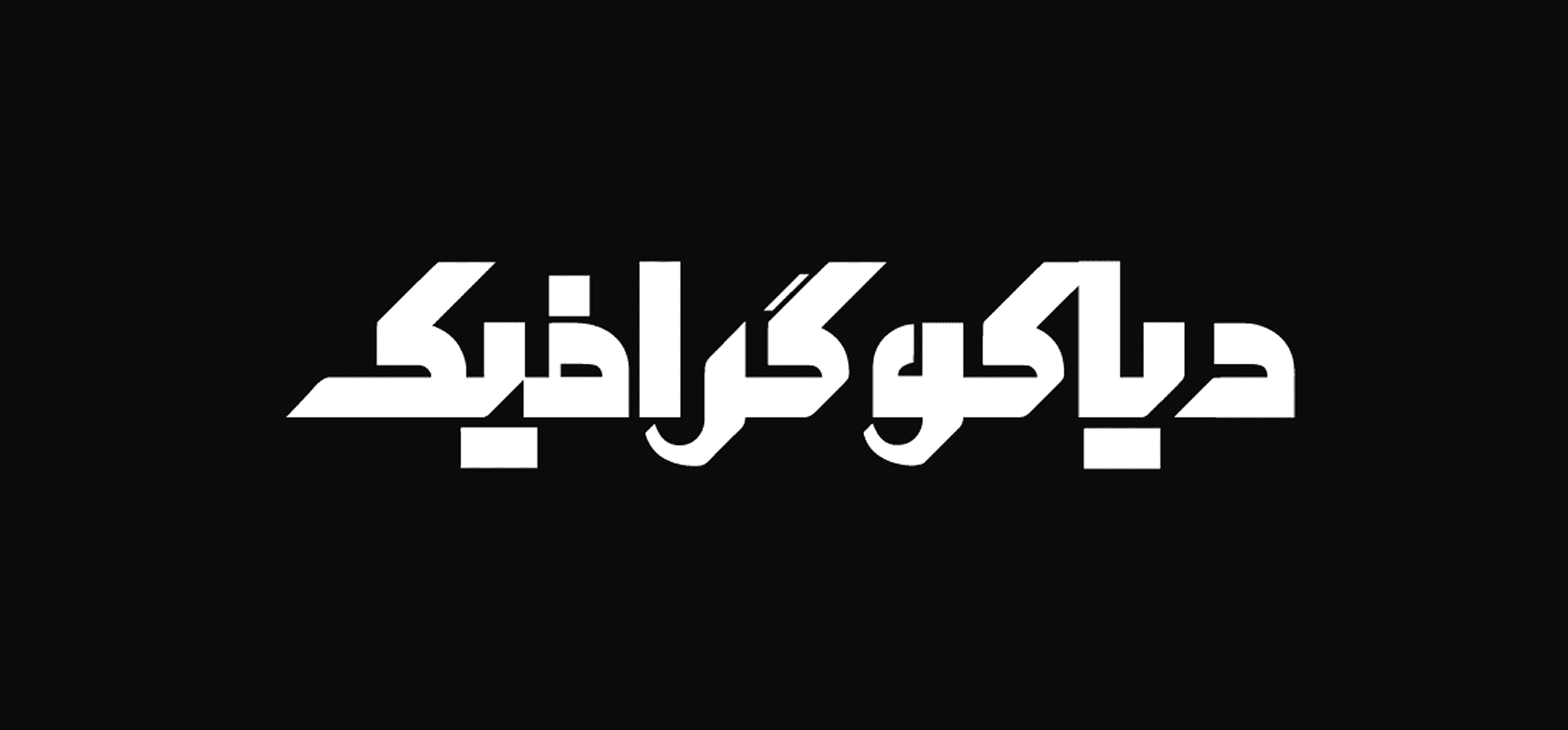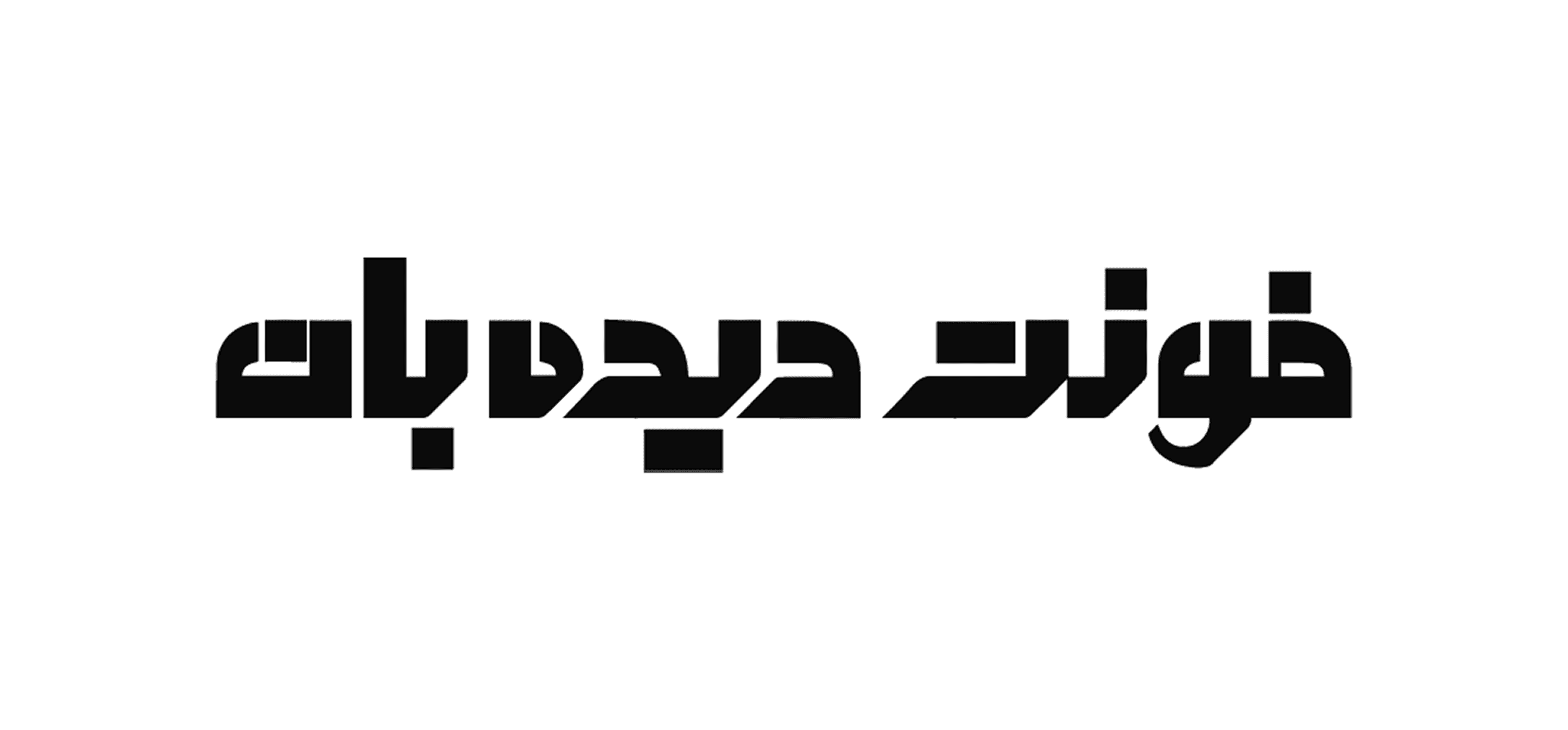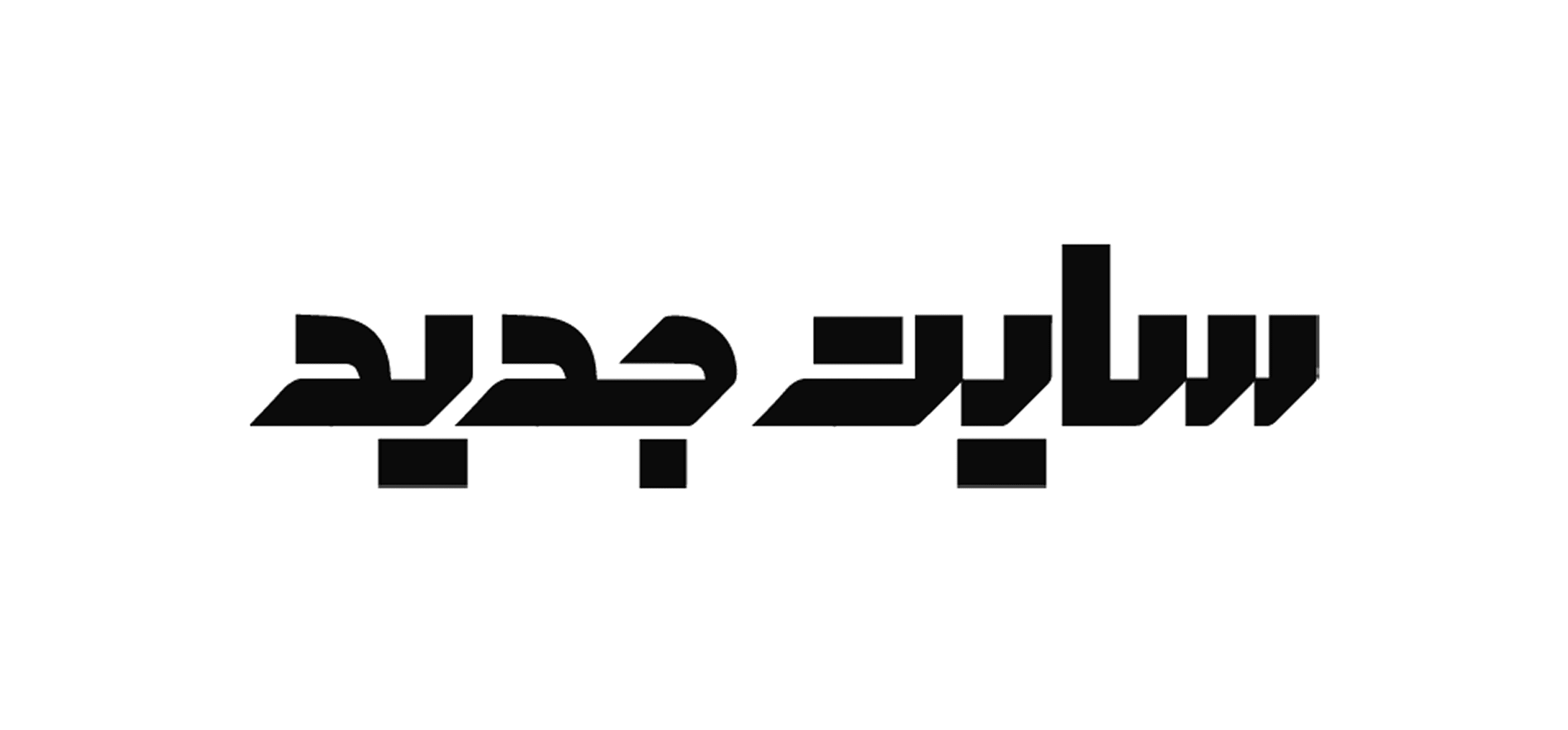
خط فارسي "ديدهبان" وتايبوغرافياه مصمَّم للاستخدام في مشاريع التيبوغرافي الاحترافي وتصميم شعارات النص (لوغوتايب) الفارسية والإيرانية، ويُسهّل عمل المصممين وكذلك غير المتخصصين في التصميم.
أبرز ميزاته:
يُمكِّنك بسهولة من تصميم لوغوتايب جذاب لأعمالك وموقعك الإلكتروني.
يتمتّع الخط ببنية عريضة وسميكة (Bold) تمنحه حضورًا قويًا في التصميم.
يظهر هذا الوضوح والقوة بصريًا في العرض التمهيدي للخط.
بفضل هذه الخصائص، يُعتبر "ديدهبان" خيارًا مثاليًا لأي مشروع يتطلب لفت الانتباه بصريًا من خلال النص.